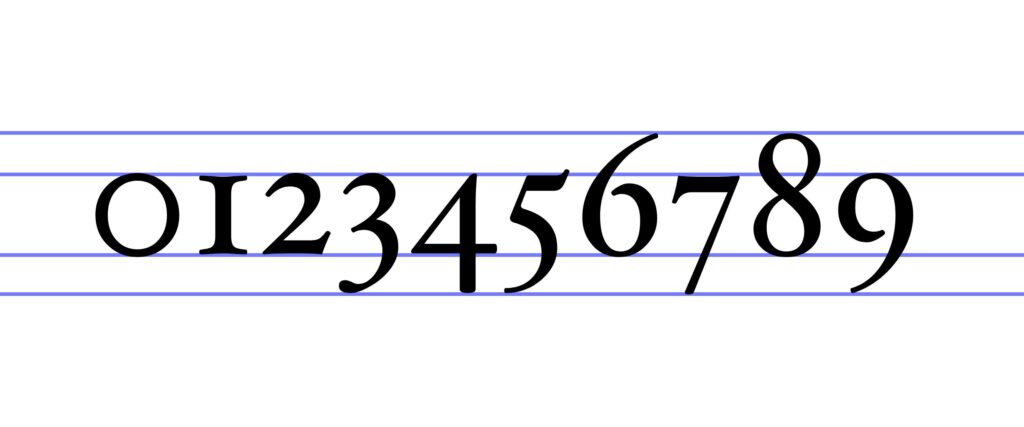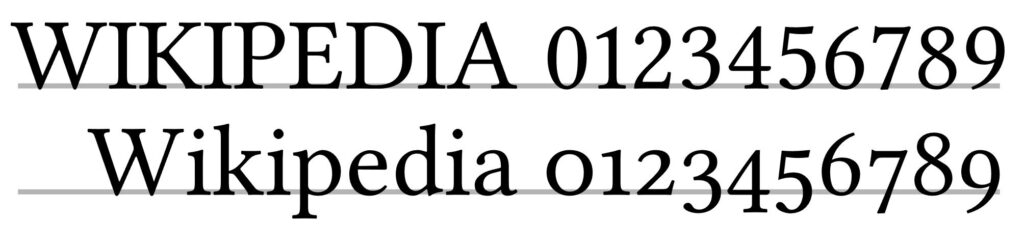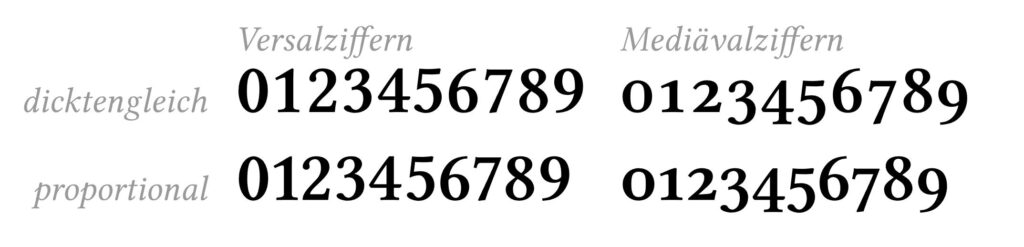
Zahlen
Arabische Zahlen
Unser heutiges Zahlensystem basiert auf arabischen Ziffern, die ursprünglich aus Indien stammen. Während Griechenland und Rom als Wiegen der Buchstaben gelten, ist Indien die Wiege der Mathematik. Über die arabische Welt – mit der entscheidenden Einführung der Null – gelangte das System im Mittelalter über Spanien nach Europa und setzte sich durch seine Einfachheit gegen die römischen Zahlen durch.
Römische Zahlen
Die Zeichen I, V, X, L, C, D und M prägten über Jahrhunderte den römischen Kulturraum. Sie erwiesen sich jedoch für komplexe Berechnungen als unpraktisch. Heute werden sie nur noch in speziellen Kontexten genutzt, etwa bei Kapitelnummerierungen, Zifferblättern oder dekorativen Anwendungen.
Stellenwertsystem
Die Stärke der arabischen Zahlen liegt im dezimalen Stellenwertsystem: Jede Position innerhalb einer Zahl entspricht einer Potenz von zehn (Einer, Zehner, Hunderter usw.). Dieser klare Aufbau erleichtert das Rechnen erheblich und war ausschlaggebend für die Verbreitung des Systems.
Mediäval- und Versalziffern
Mit der Entwicklung von Mediävalziffern im 16. Jahrhundert schuf Claude Garamond Zahlen, die sich harmonisch in den Fließtext einfügen – mit Ober- und Unterlängen, ähnlich wie Kleinbuchstaben. Im Gegensatz dazu stehen Versalziffern, die die volle Versalhöhe einnehmen und durch ihre einheitliche Breite besonders für Tabellen und Formulare geeignet sind. Während Mediävalziffern im Zuge der Digitalisierung seltener wurden, erleben sie heute wieder Beachtung, da sie Texte lebendiger und lesefreundlicher wirken lassen.